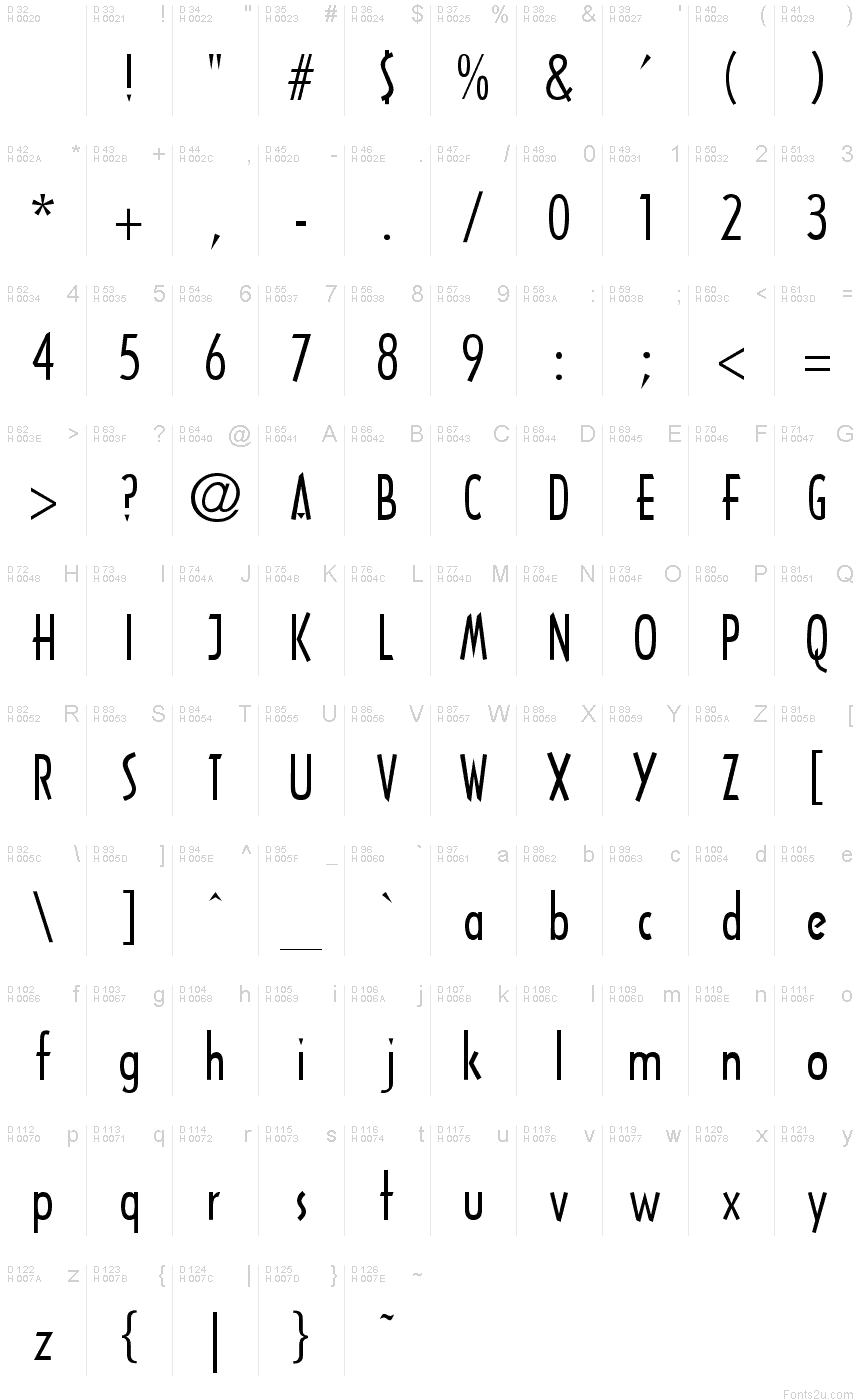
Arcitectura od A. Carr Remember to darmowy, bezszeryfowy krój pisma, którego litery układają się niczym panorama miasta – są wysokie, wąskie i ostro cięte. Przesadne piony i lekko dziwaczne krzywizny nadają mu techniczny charakter, jakby każdy znak został narysowany pisakiem kreślarskim. Napięcie między surową strukturą a zabawnymi detalami sprawia, że nagłówki stają się precyzyjne i wyraziste.
Arcitectura oferuje mocny, wznoszący się rytm, który przyciąga wzrok ku górze, dzięki czemu świetnie sprawdza się na plakatach, okładkach książek, w identyfikacji wizualnej studiów architektonicznych lub projektowych, okładkach albumów oraz w wyrazistych logotypach. Ten darmowy font najlepiej prezentuje się w dużych rozmiarach, gdzie jego smukłe proporcje i ostre kształty mogą naprawdę odetchnąć. W przypadku tekstów ciągłych lub podpisów, połącz Arcitectura z czystym, neutralnym krojem groteskowym, aby zachować czytelność i wizualną równowagę projektu.